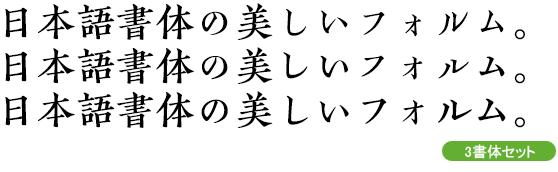
宋朝体
KOこみなみ陳起M
KOKoMinamiChinki-M
名古屋の活字鋳造会社「津田三省堂」の私家版『本邦活版開拓者の苦心』(津田三省堂、1934年)から復刻した彫刻の趣の残った書体「みなみ」を小ぶりにした和字ドーンスタイル「こみなみ」に、中国・南宋時代に陳起(生没年不詳)によって刊行された『南宋羣賢小集』(陳宅書籍舗刊、1208年−1264年)から復刻した宋朝体「陳起」、15世紀の印刷者ニコラ・ジェンソン(1420?−1481)が製作した活字が用いられている『博物誌』(1472年)から復刻したヴェネチアンローマン体「K.E.Aries Medium」を組み合わせた日本語書体です。